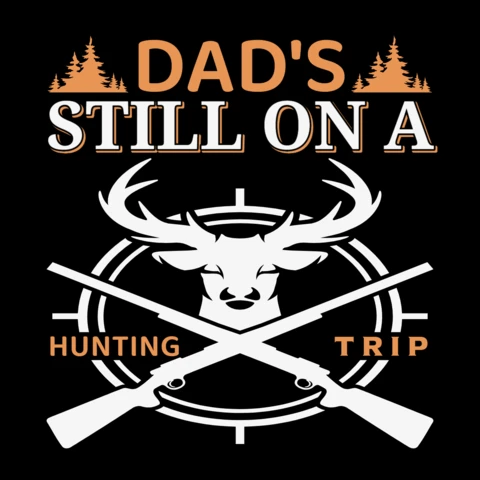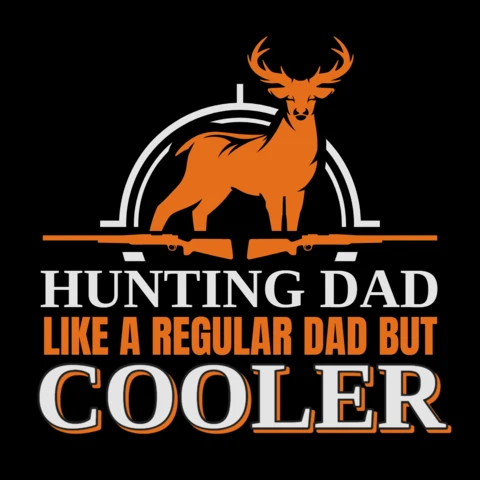
Modèle de conception de chasse rustique avec typographie audacieuse et motif animalier
Éditer dans Design Studio Télécharger en JPGLibérez votre esprit d'aventure grâce à notre modèle de design de chasse rétro, qui présente une typographie audacieuse et des motifs de cerfs enjoués, parfaits pour les vêtements, les autocollants et les produits de merchandising de plein air !